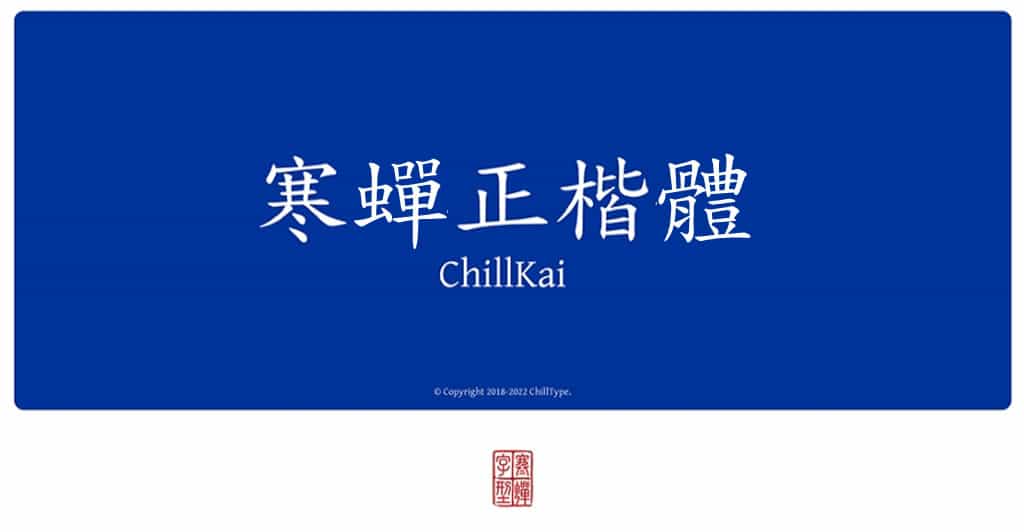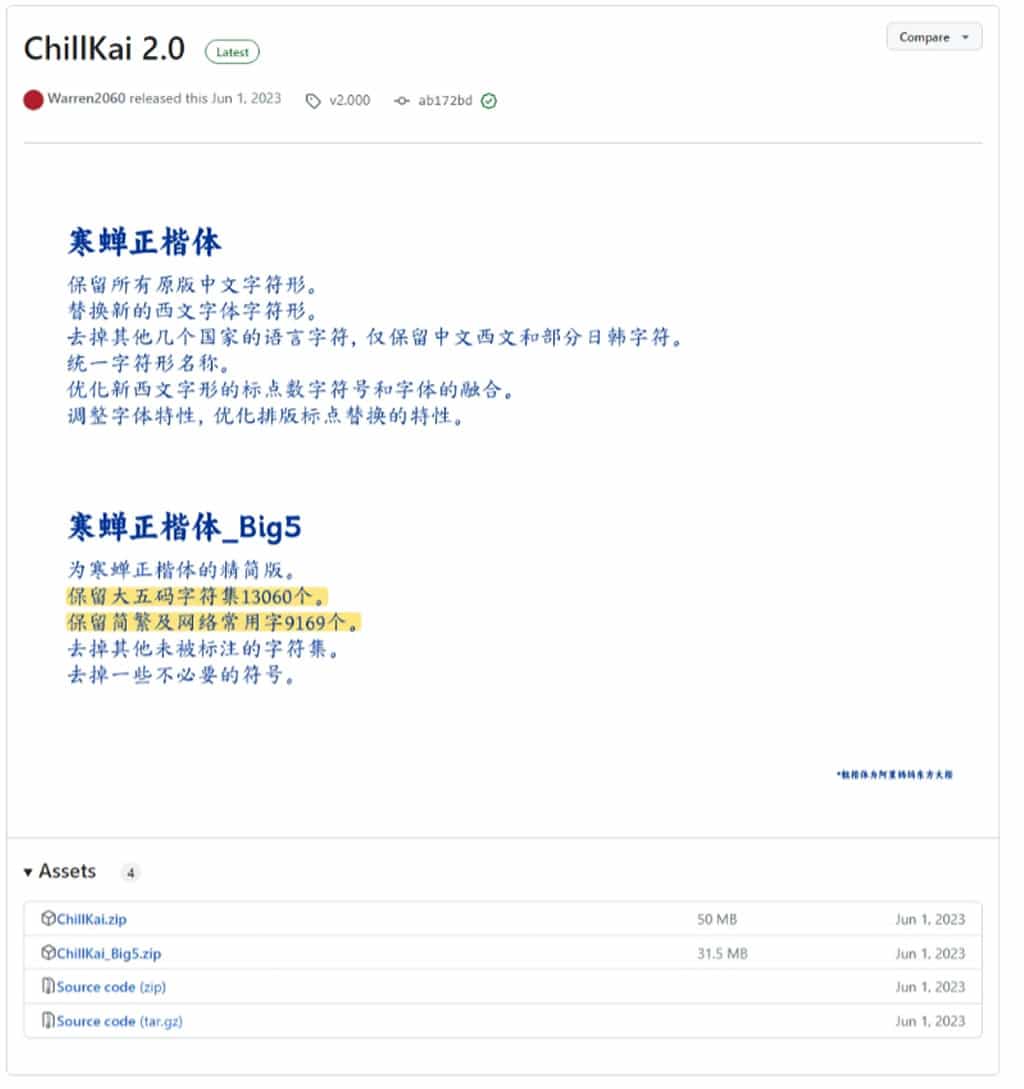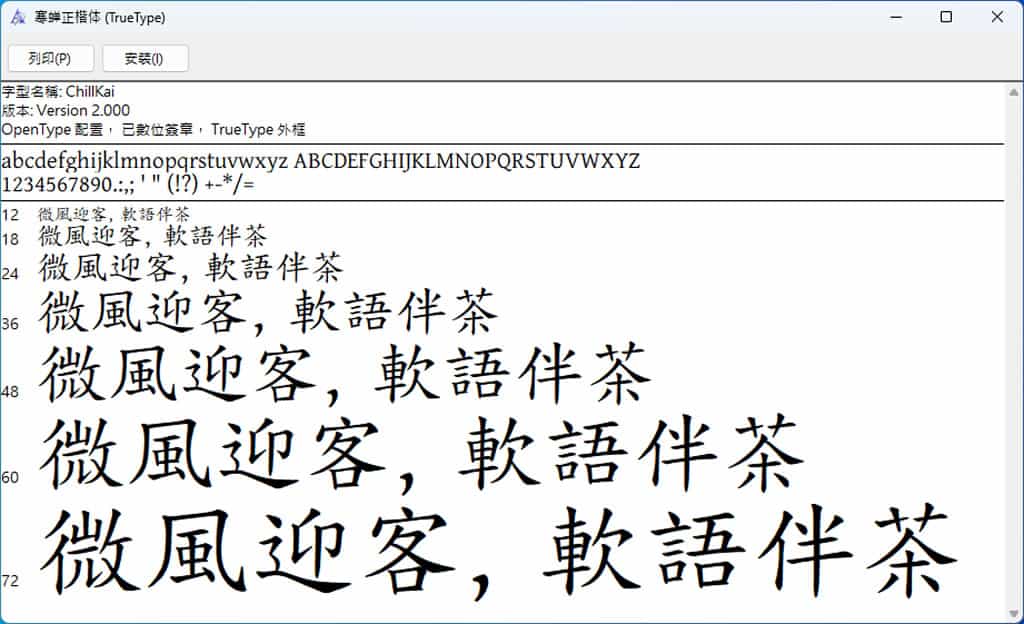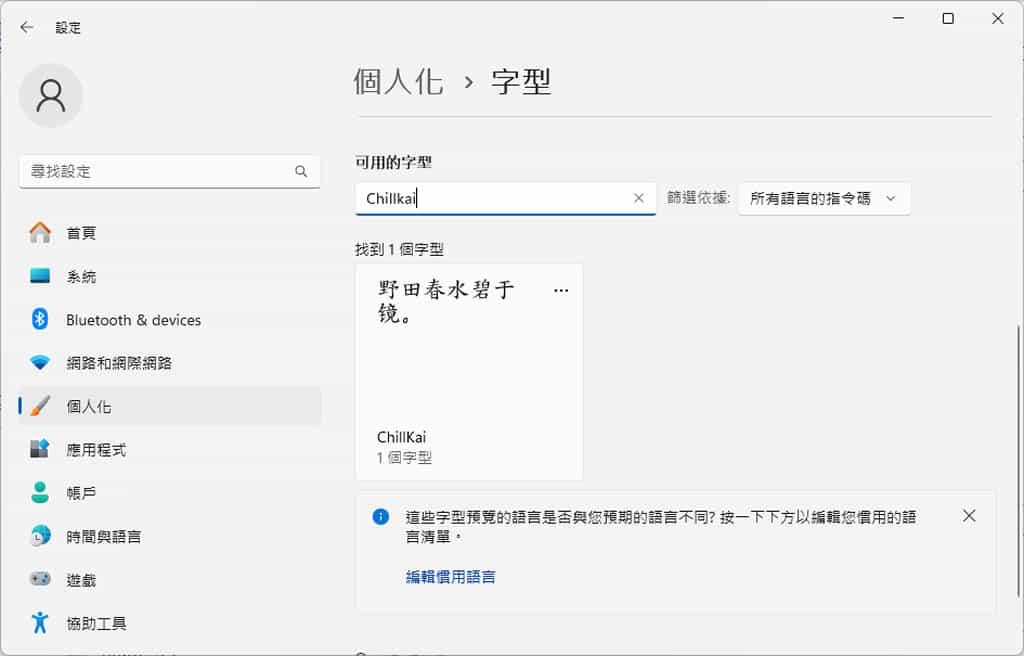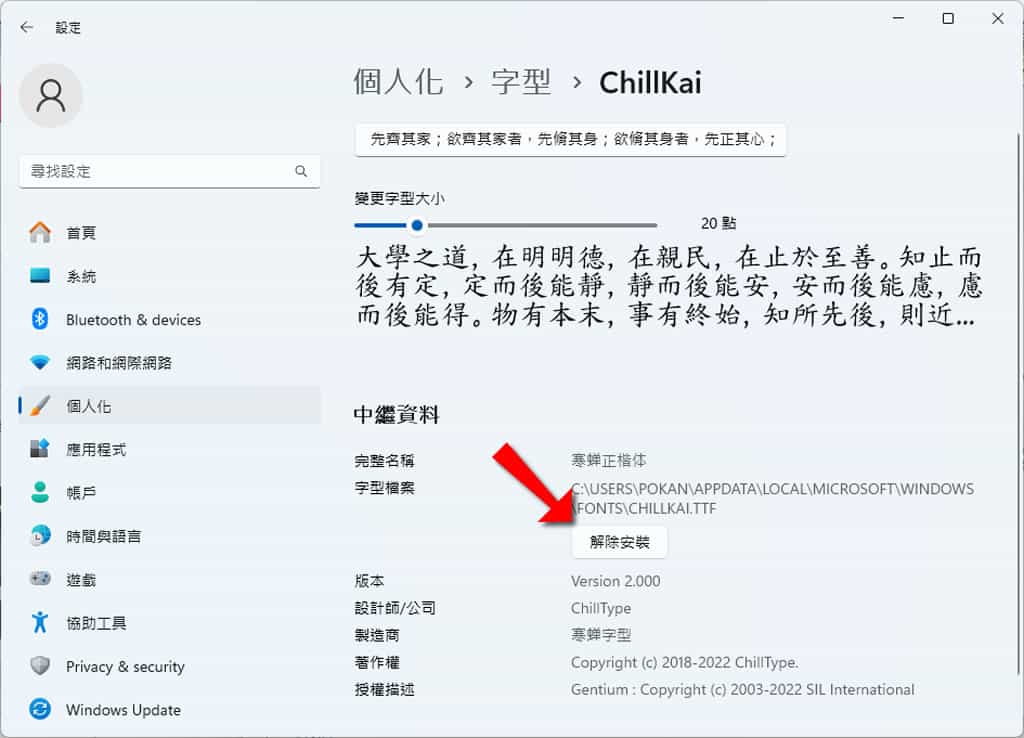
「寒蟬正楷體」是一個融合「全字庫正楷體」和「Gentium」東西方兩種字體修改而成的免費楷書字型,支援簡體和繁體中文。根據作者的說明,全字庫正楷體因其字符的豐富性和多語言支持,成為了中文楷書的優秀代表。然而,其西文字體部分與中文部分的融合並不十分理想,在橫排和垂直排版中也顯得稍有不足。為了解決這些問題,「寒蟬正楷體」將西文部分替換為 Gentium 字體,這是作者最喜愛的西文字體之一。Gentium 的設計與楷書風格完美契合,無論是在與文鼎 U 楷體還是其他楷書字體的搭配中,Gentium 都能提供更加和諧統一的視覺效果。這使得「寒蟬正楷體」在中文和西文的結合上比原始字體更加流暢和一致。「寒蟬正楷體」採用 SIL Open Font License 1.1 授權,無論是個人還是企業都可以自由地將其用於商業用途,且無須知會或標明原作者
兼具中西文字體美感的免費商用楷書字體